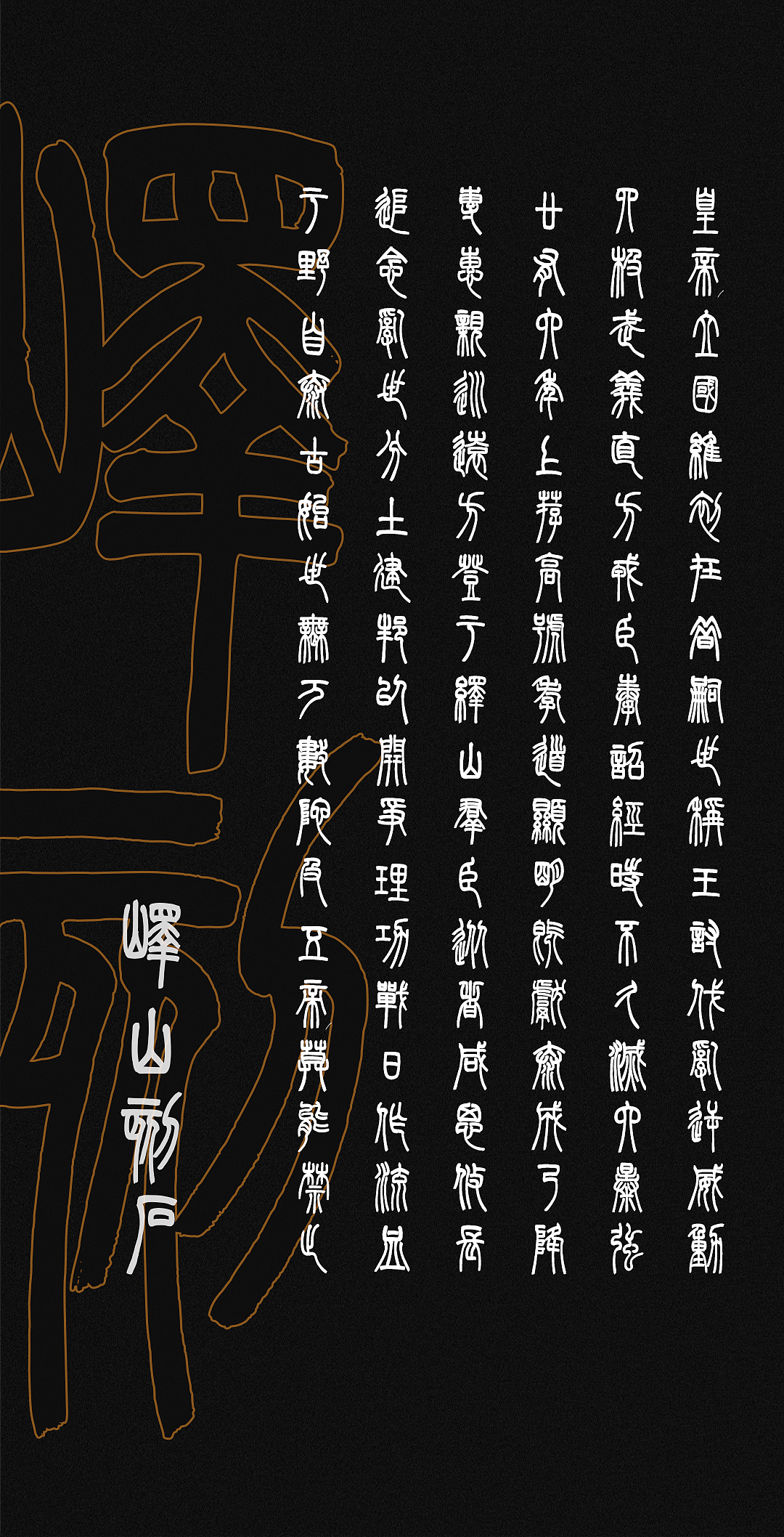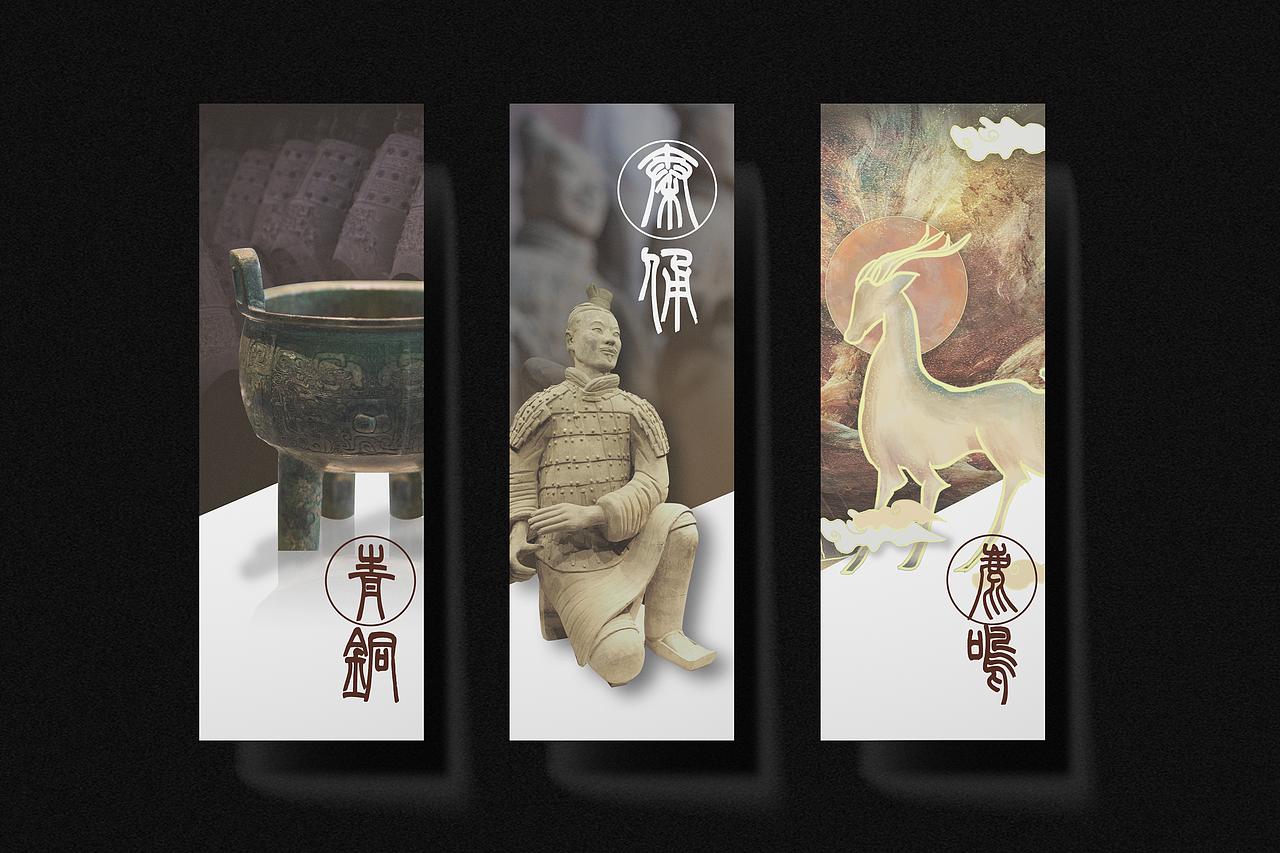
国潮设计,仿古小篆书法字体 | 字魂游龙篆书
字魂游龙篆书是华夏王朝系列字体中可考据的历史最为久远的一套字。
字形主要取自《说文解字》,综合参考清代篆书名家的作品,融入清代小篆的风格,有考据且不乏新意。
字体含9403个汉字字符,以繁体汉字为主。
除了传承延续小篆这一种字形文化,字魂网作为设计师的创意字体库,还希望通过字库化设计和设计师的奇想,让其像封神榜等传统文化一样,能够在现代迎来新一轮的生机,成为新潮、实用、有内涵、标志性的美学,融入现代人们的生活中。